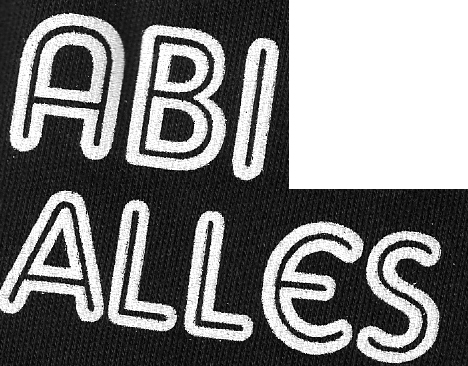
Schrift mit E wie C mit STricht
such folgende Schriften. sind 2 verschiedene zumindest die A sind verschieden !
Besonders sehen das E und das N aus !
das sieht für mich irgendwie nach freefont aus (also auch der umstand, dass niemand die schrift zu kennen scheint). schau doch mal bei dafont & co…
ja, das N sieht ganz besonders aus – ganz besonders in dem bild!